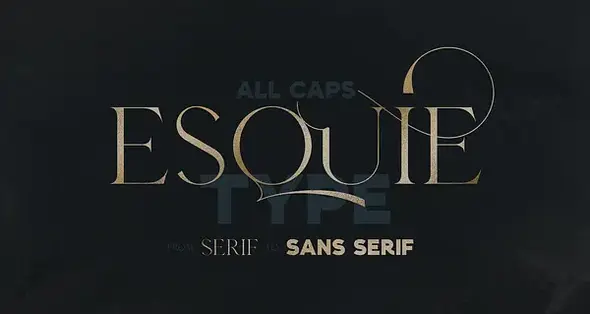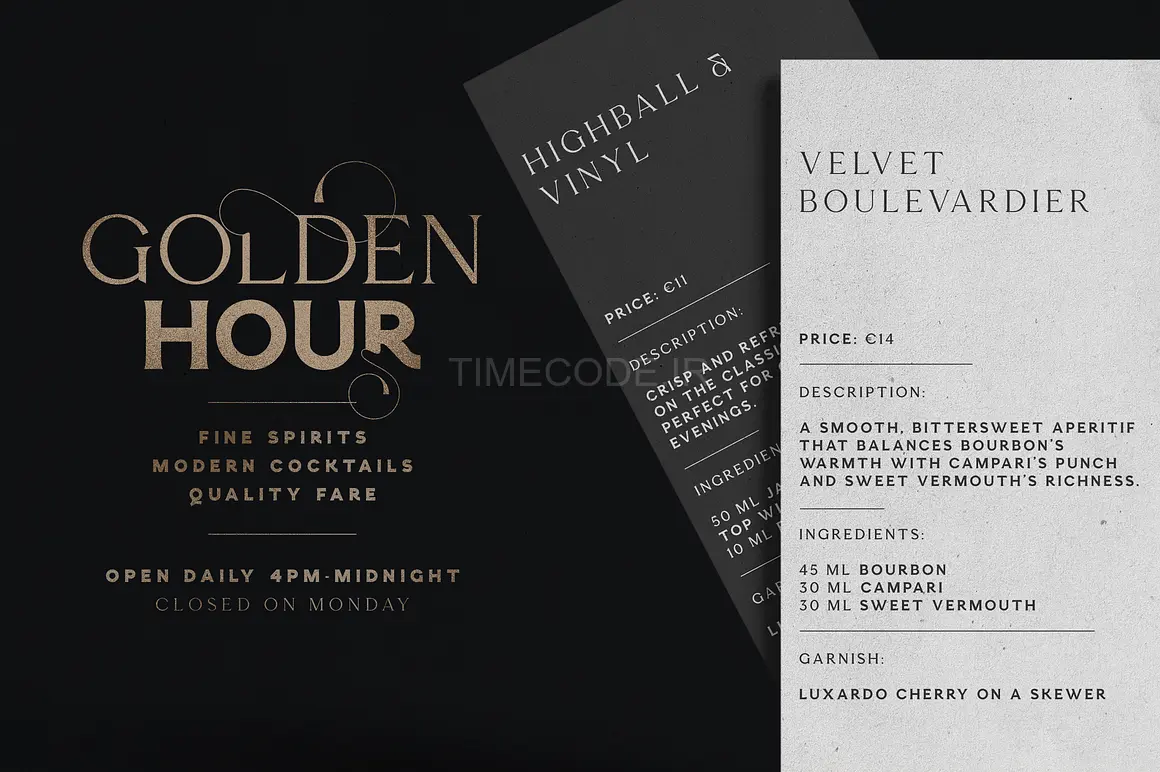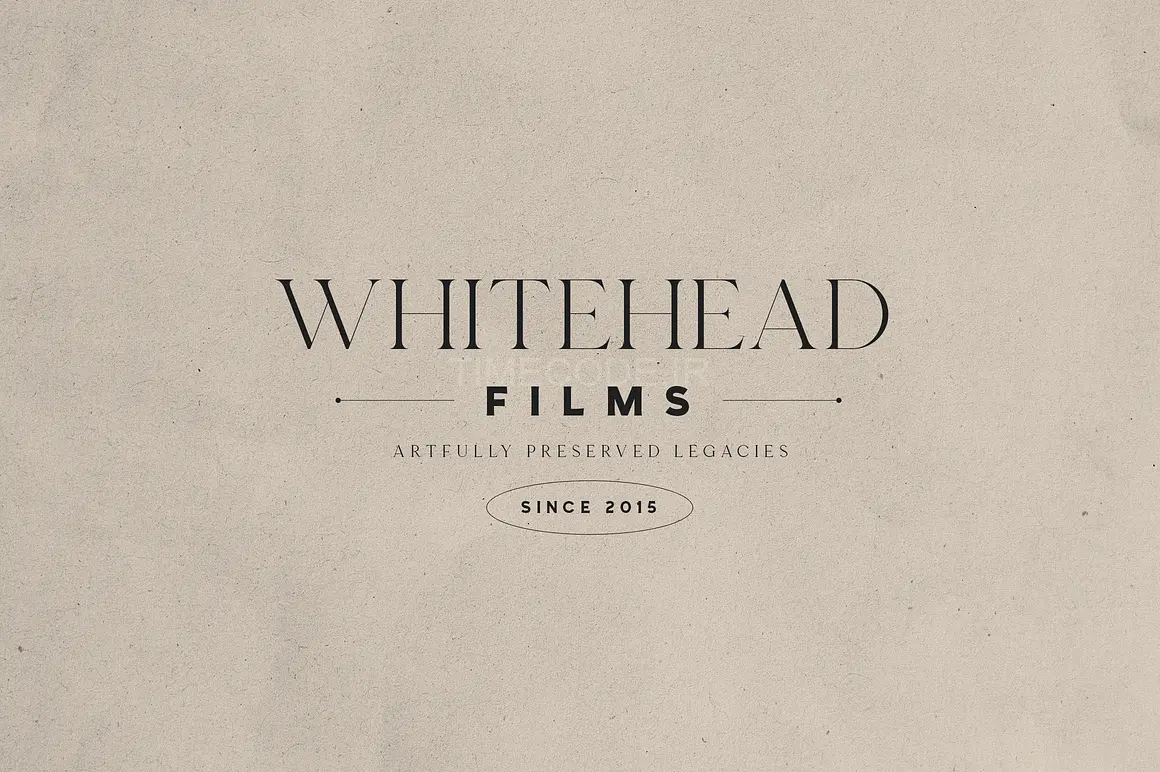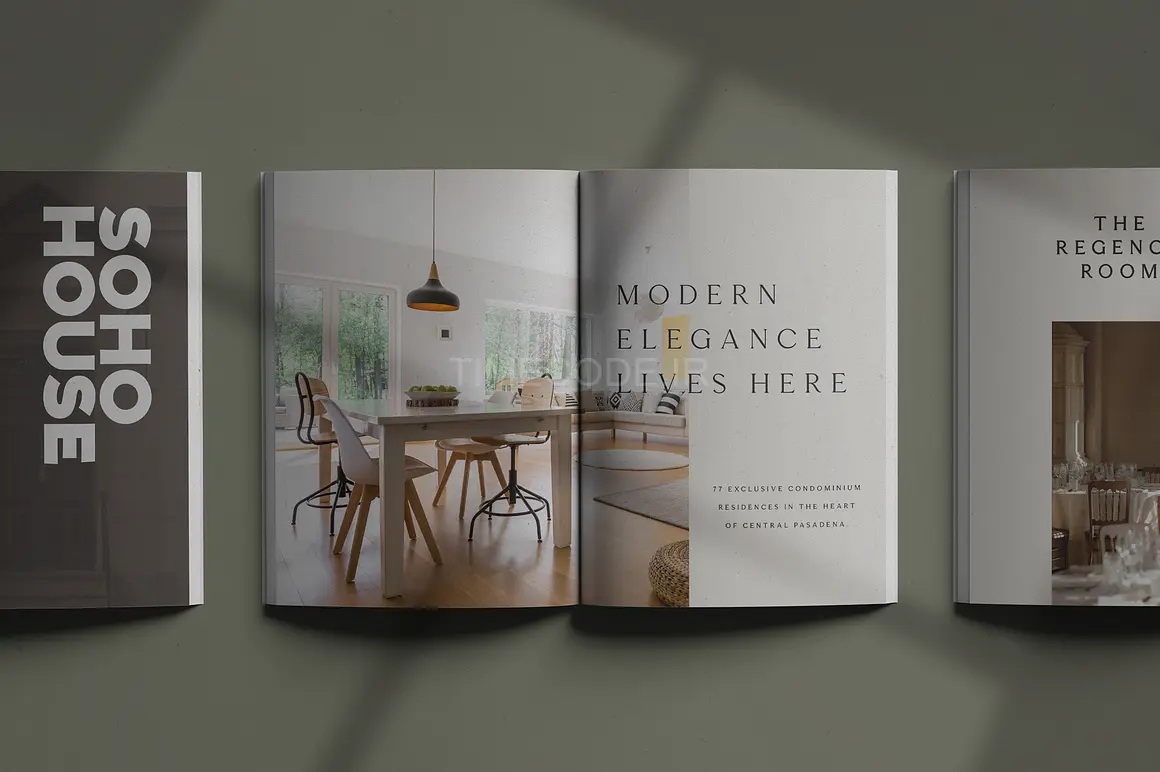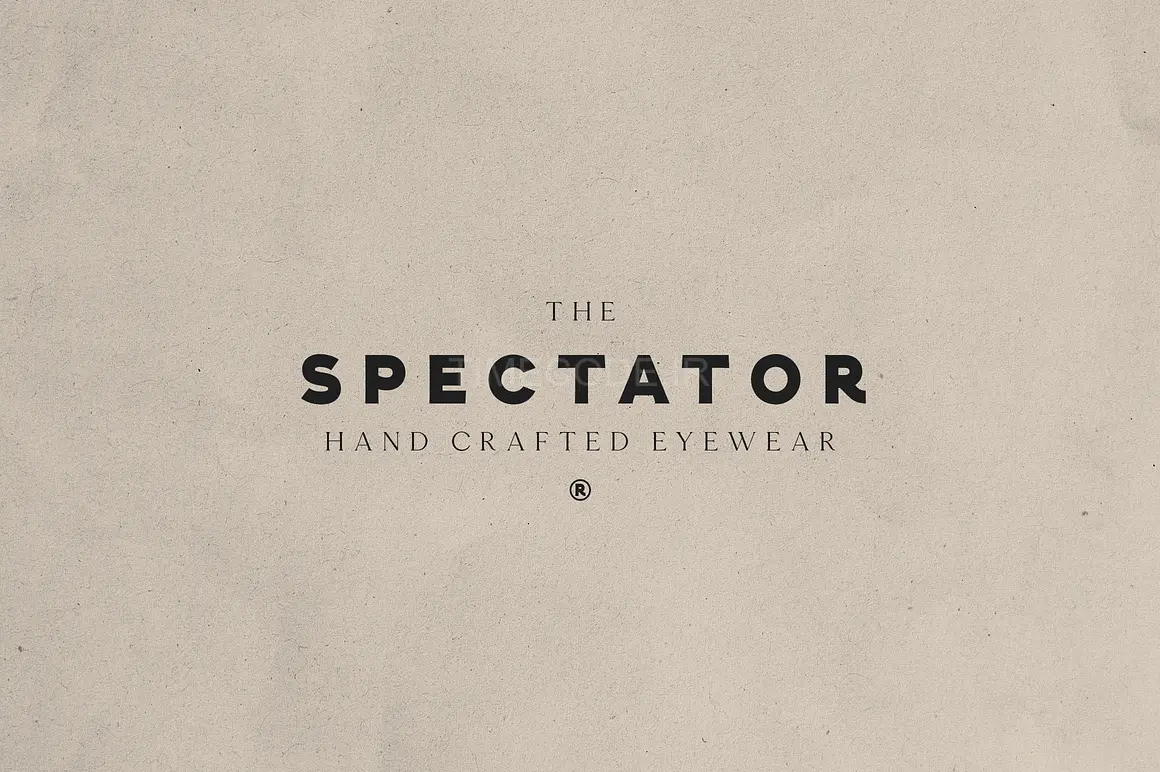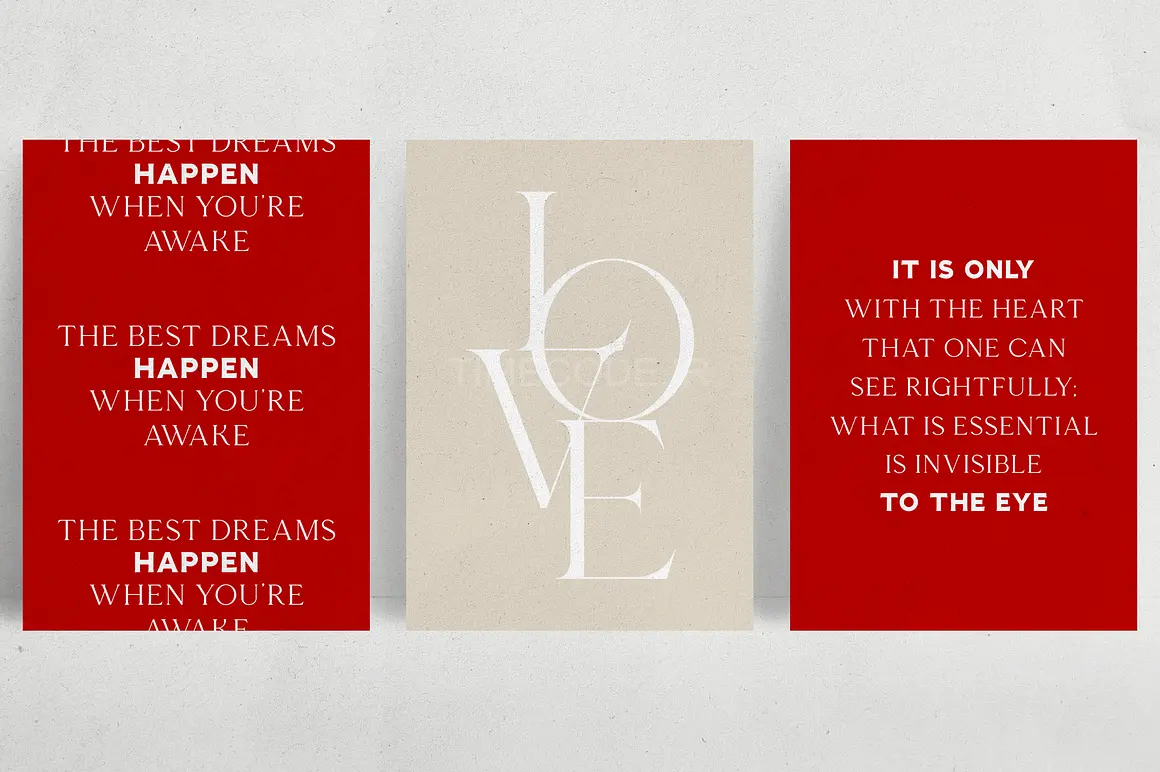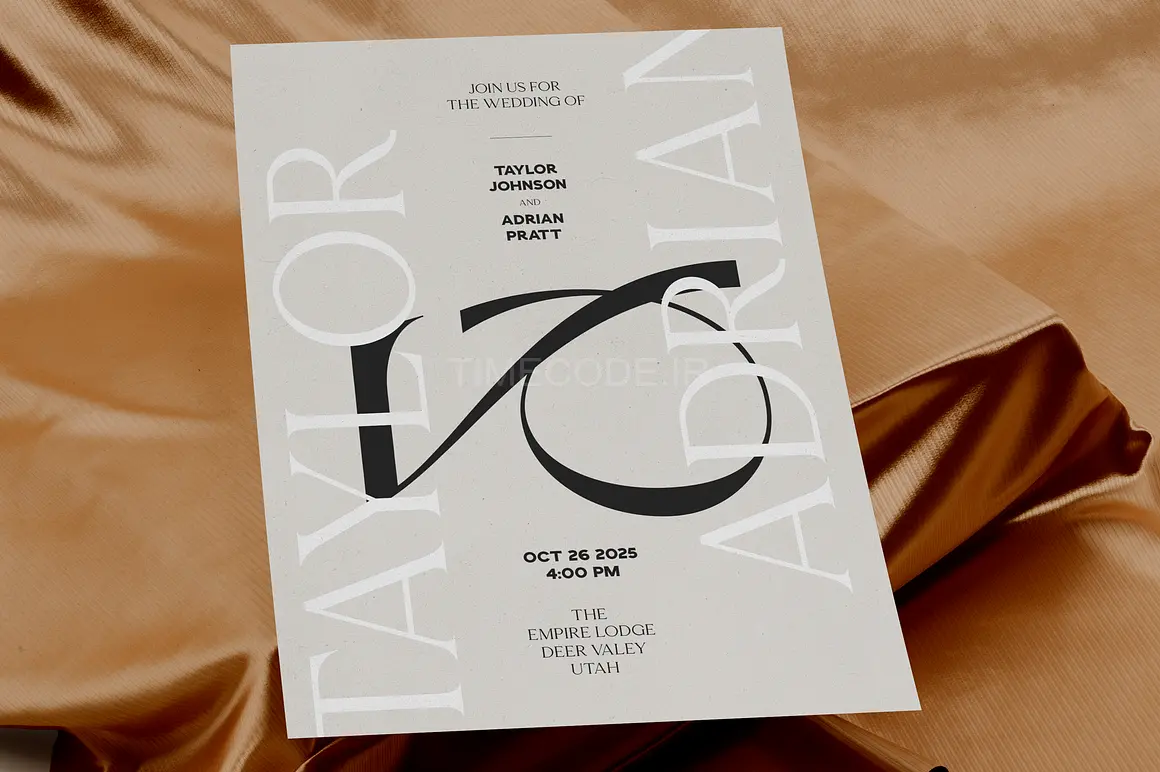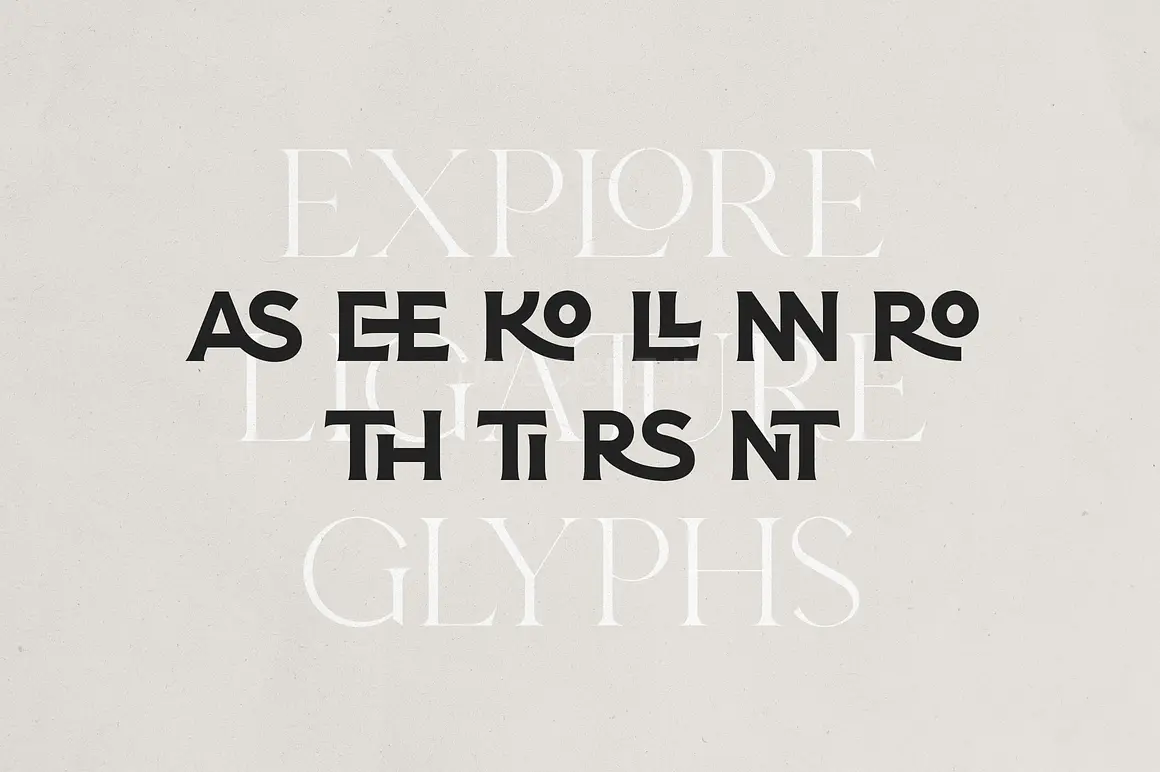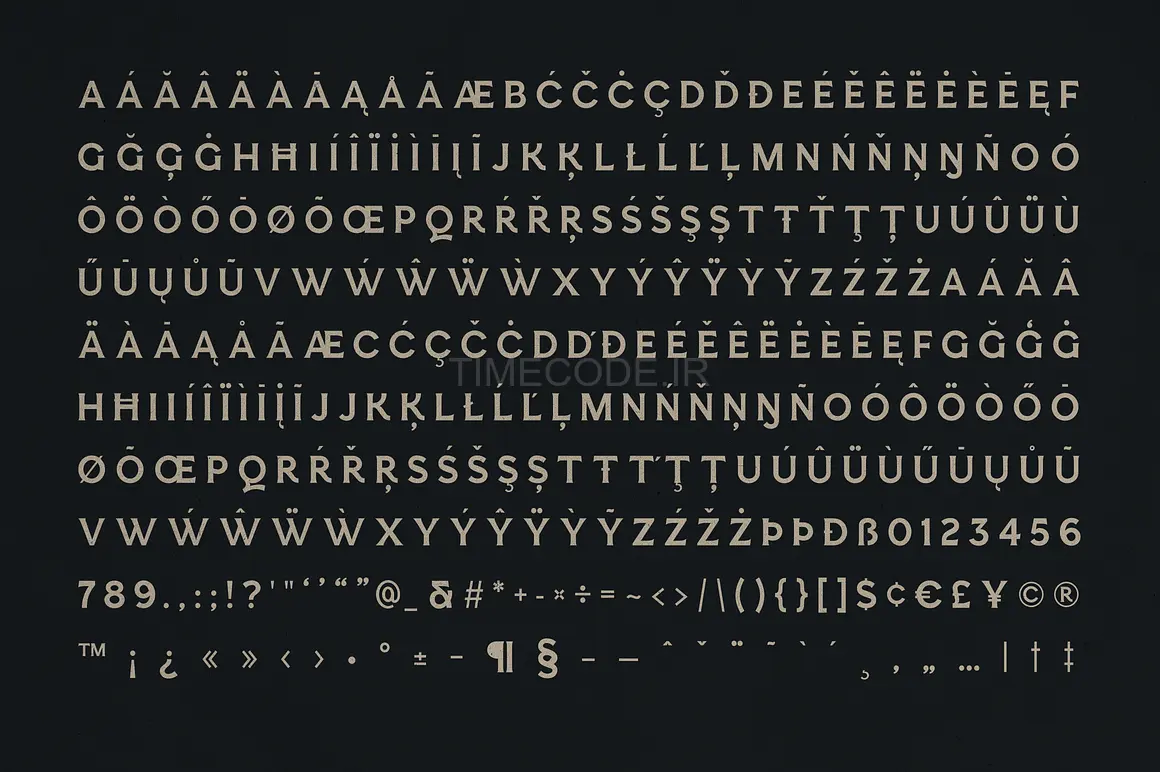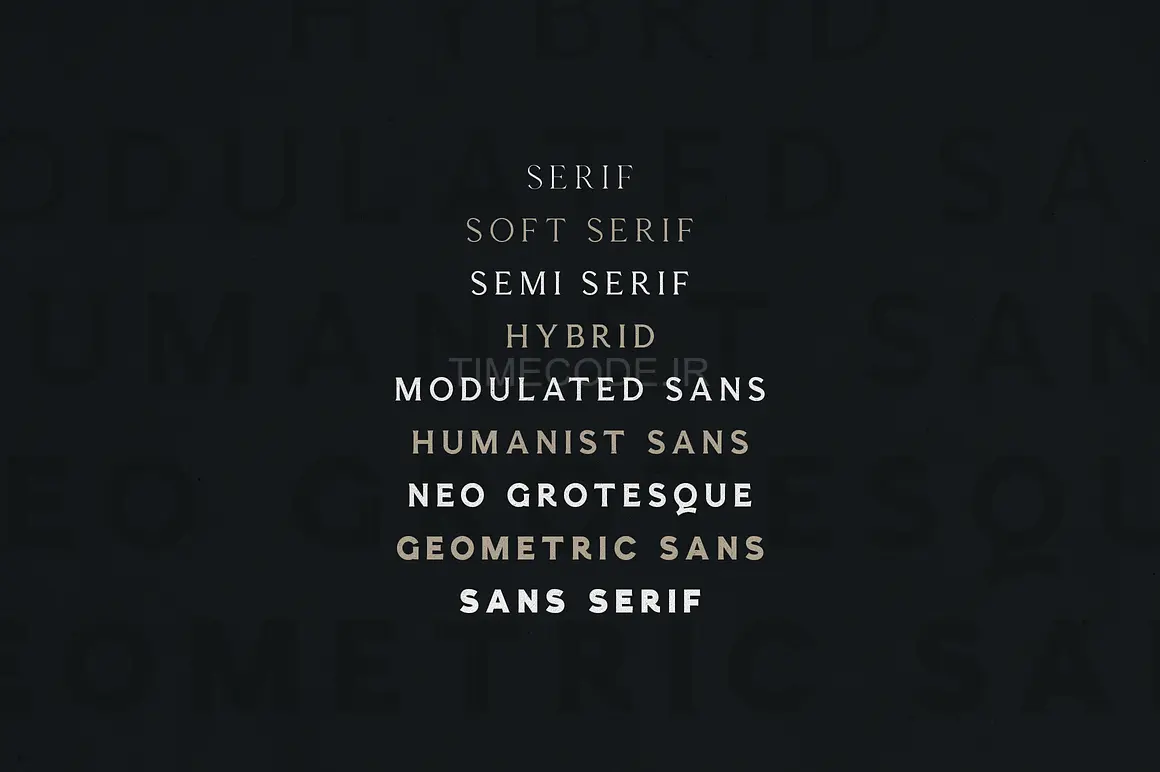
• Esquie - From Serif To Sans Typeface
از ظرافت سریف تا سادگی سنس. Esquie یک تایپ‌فیس تجربی تمام‌حروف بزرگ است که زیبایی بی‌زمان سریف‌ها را با وضوح جسورانه سنس‌سریف‌ها پیوند می‌زند. Esquie که به عنوان یک سفر تایپوگرافیک طراحی شده، ۹ استایل استادانه را ارائه می‌دهد که به آرامی از سریف کلاسیک به سنس‌سریف شیک تغییر می‌کنند – و آن را به ابزاری قدرتمند برای برندسازی، طراحی سرمقاله، و بیان خلاقانه تبدیل می‌کند.
• ۹ فونت که یک تحول تدریجی از سریف به سنس‌سریف را نشان می‌دهند
• پشتیبانی کامل از بیش از ۸۵ زبان از جمله اسکریپت‌های لاتین
• ویژگی‌های تایپوگرافیک: گلیف‌های لیگچر و فرم‌های جایگزین حروف
• فرمت کاملاً متغیر برای کنترل دقیق و استایل‌های بی‌نهایت میانی
• تمام حروف بزرگ
مناسب برای:
• برندسازی لوکس، جلد کتاب، طرح‌بندی‌های سرمقاله، بسته‌بندی بوتیک، گالری‌های هنری، مؤسسات فرهنگی، و هر طرحی که هم ظرافت و هم تمایز را طلب می‌کند.
چرا طراحان Esquie را دوست دارند:
• از ضربه‌های ظریف با کنتراست بالا گرفته تا فرم‌های مدرن مینیمالیستی، Esquie با لحن پیام و هویت بصری شما سازگار می‌شود. این فقط یک فونت نیست – یک سیستم طراحی است.
✦ Esquie — The Evolution of Elegance ✦
From Serif Grace to Sans Simplicity | All-Caps Variable Typeface | 9 Fonts
Esquie is an experimental all-caps typeface that bridges the timeless beauty of serifs with the bold clarity of sans-serifs. Designed as a typographic journey, Esquie offers 9 masterfully crafted styles that transition seamlessly from classic serif to sleek sans-serif — making it a powerful tool for branding, editorial design, and creative expression.
- 9 fonts showing a progressive transformation from serif to sans-serif
- Full support for 85+ languages including Latin-based scripts
- Rich typographic features: ligature glyphs and alternate letterforms
-Fully variable format for precise control and infinite in-between styles
- ALL CAPS — with character!
Perfect For:
Luxury branding, book covers, editorial layouts, boutique packaging, art galleries, cultural institutions, and any design that demands both elegance and edge.
Why Designers Love Esquie:
From graceful high-contrast strokes to minimalist modern forms, Esquie adapts to your message’s tone and visual identity. It’s more than a font — it’s a design system.